バリアフリカレンダー2020
視覚障害のある方と晴眼者との穏やかな“共生”をコンセプトに、アートディレクター・関宙明氏(mr.universe)がデザインを手掛けるバリアフリーカレンダーは、日常使いに適したシンプルなデザインと、誰もが使う心地よさを感じられるバリアフリーに配慮した浮き出し文字のカレンダー。近年、加齢や病気によって増加傾向にある中途視覚障害の方の点字習得の難しさを背景に、それまで慣れ親しんだ文字・数字の形を真美堂独自の特殊加工である浮出し文字で表現し、目(視覚)と指(触覚)のどちらからでも読むことを可能にした。2015年版の発売開始から、視覚障害のある方や晴眼者の方も問わず、毎年好評を得ている。
「バリアフリカレンダー2020」特長
読みやすく美しい立体的な文字
これまで多くの視覚障害のある方へリサーチを重ね、50種以上の用紙と、版、圧力の試行を繰り返した結果、触って読み取れる文字の高さを実現した。さらに、文字・数字に使用するフォントにも着目。触ったときの読みやすさと視覚的な美しさを兼ね備えた「フォアフィンガー書体」を採用している。
シンプルさが心地よいミニマルなデザイン
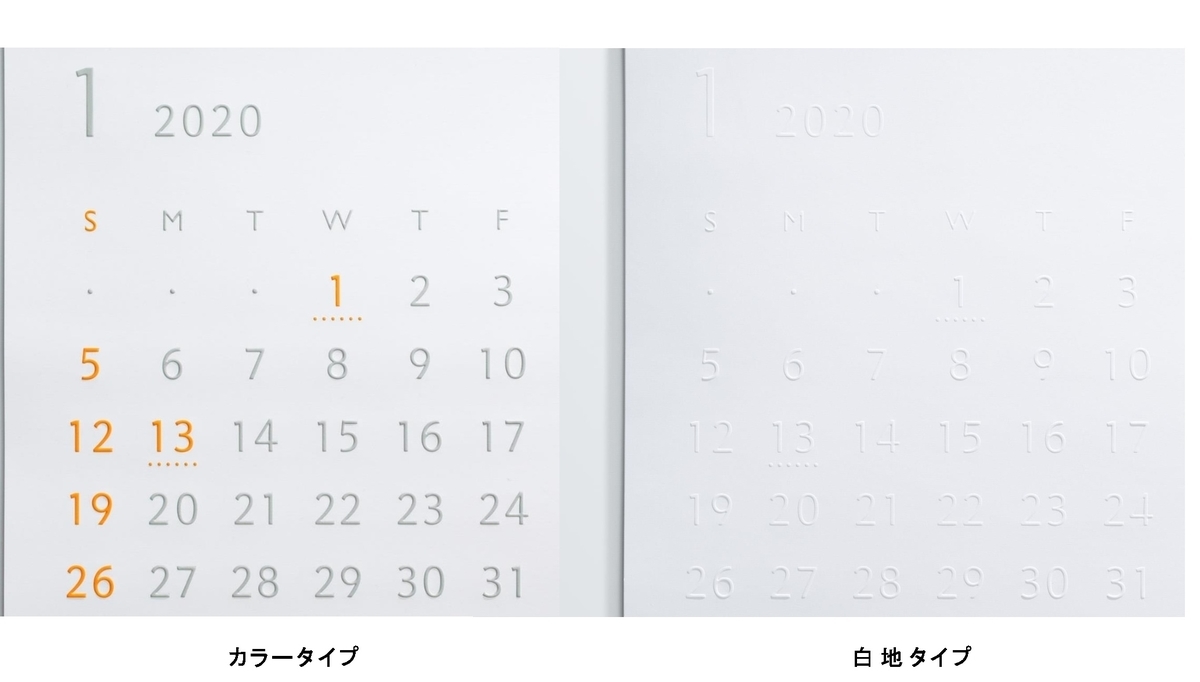
カレンダー本来の読む使いやすさはもちろん、そのデザイン性の高さも魅力のひとつ。飾るシーンや場所を選ばないシンプルなデザインで、部屋のインテリアとして生活に自然に溶け込む。
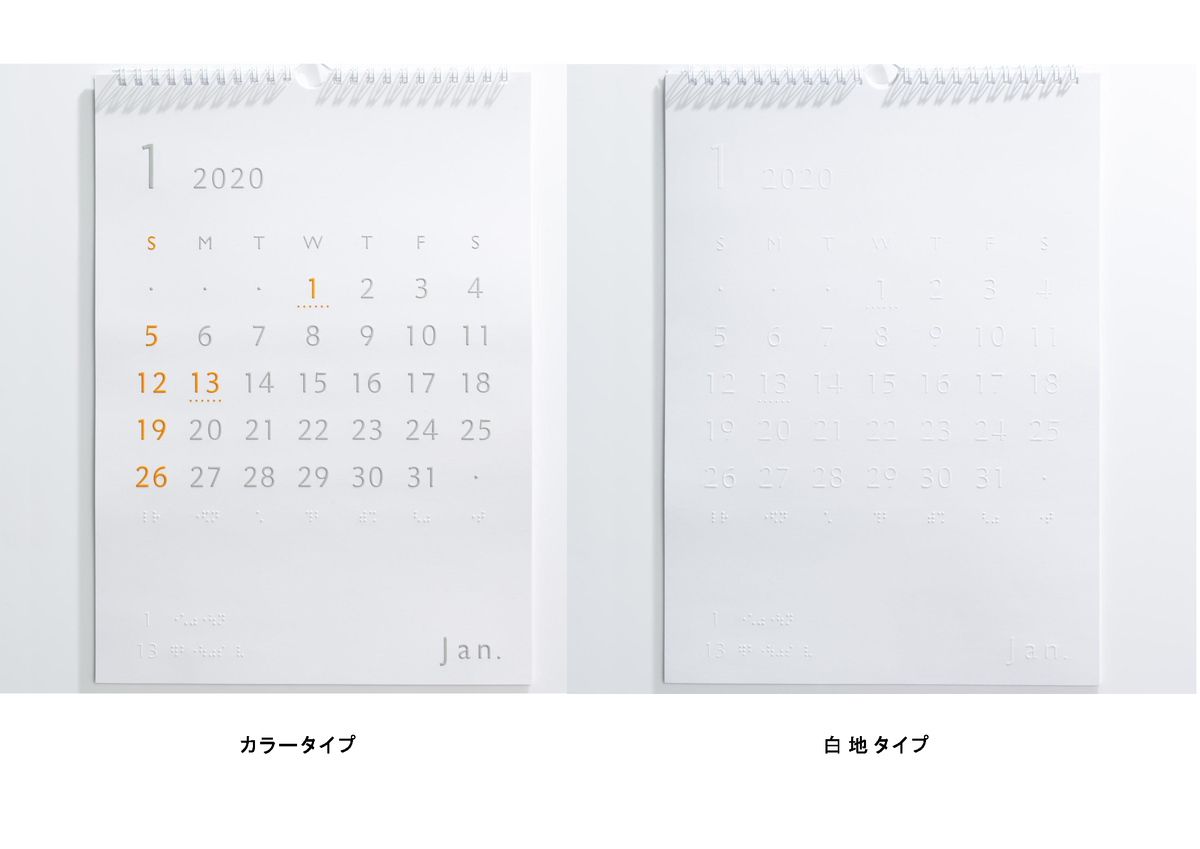
6年目を迎える今回も、オレンジとグレーの落ち着いた配色がやさしいカラータイプと、白地の用紙に浮き出された立体的な文字を光の陰影で楽しむ白地タイプの2種類を用意。カラータイプにも浮き出し加工を施している。
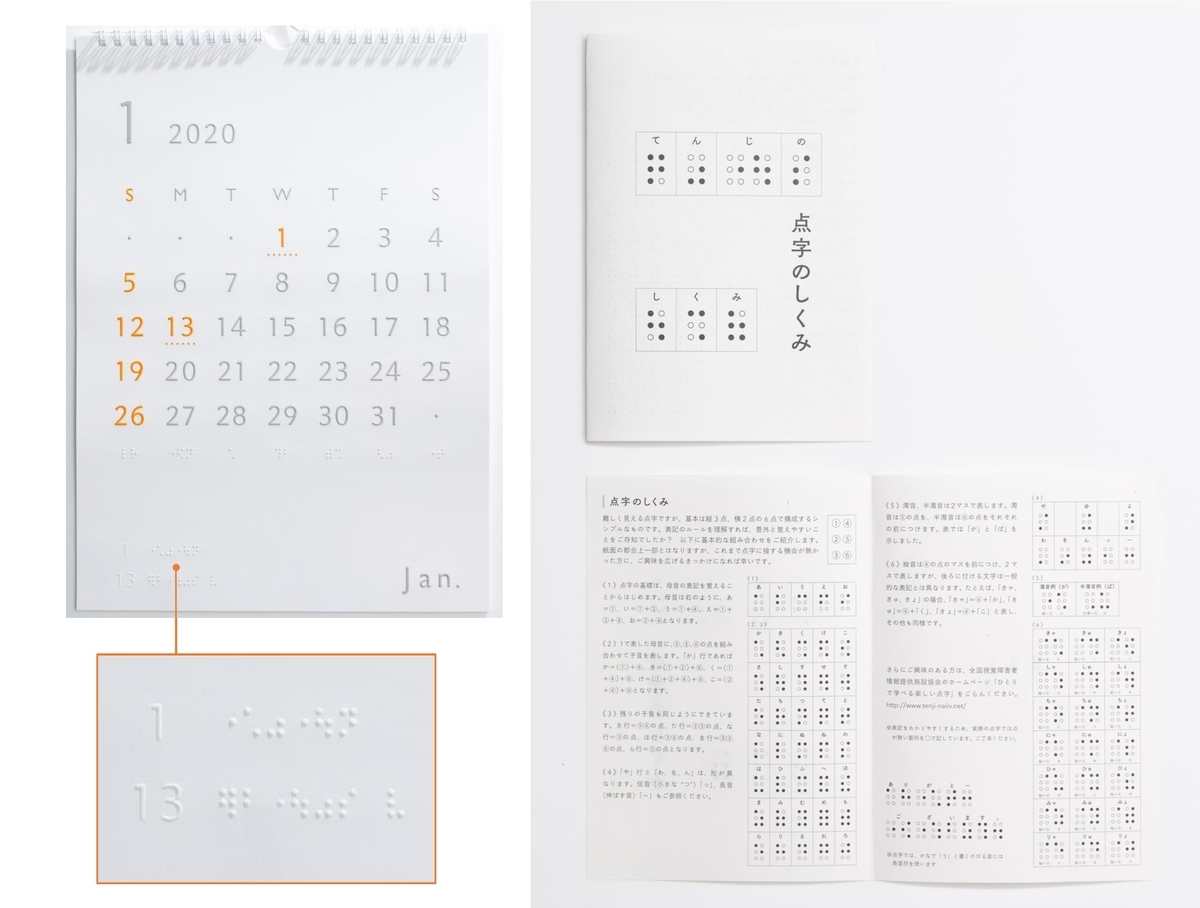
浮き出し文字は点字使用の人に使えることから、バリアフリーカレンダーでは祝祭日名など一部に点字を使用している。これまで点字に触れる機会のなかった人でも身近に感じられるように、点字の基本を解説した“点字のしくみ”を表紙の裏面に掲載してきたが2020年版からは装い新たに、B6サイズのコンパクトなまとめ付録としてリニューアル。カレンダーに載っている点字を調べてみたり、洗濯機や炊飯器など身の回りにある点字を探してみたりと、使い方さまざまに点字を体験できる。